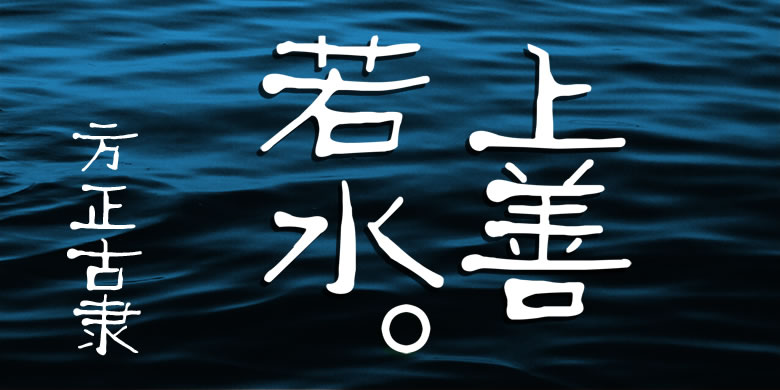
方正古隶繁体
品牌:方正字库设计师:荆鹰发行时间:2003字库编码:大陆简体(GB2312-80)、大陆繁体(GB12345-90)、简繁扩展(GBK)、港台地区(BIG-5)分类:常规书写·毛笔
方正古隶是由书法家荆鹰先生创作。这款字体是由作者自制的竹笔书写而成,原稿字宽不到一厘米,放大后笔力仍显中正雄浑,宛如用毛笔写就。其结构巧妙严谨,大小均匀重心平稳。其风格古朴典雅,极富装饰意趣,适用于文化类的宣传设计,以及商业类品牌的广告和产品包装设计。